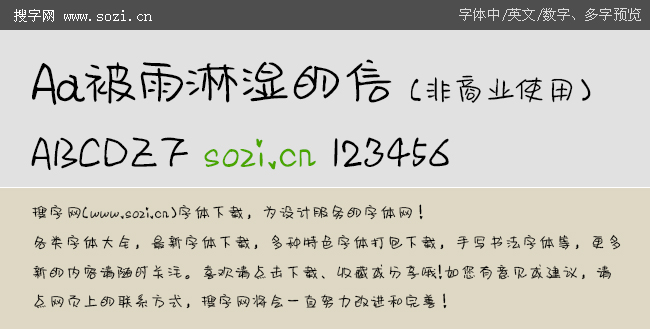
Aa被雨淋濕的信
搜字網(wǎng)給大家提供一款Aa被雨淋濕的信(非商業(yè)使用)中文字體下載,Aa被雨淋濕的信是一款卡通風格的手寫字體,這款字體筆畫略為纖細,字形圓潤可愛,富有趣味性,字體中部分英文的點被換成了可愛的愛心圖案,具有很好的視覺感。適合應用于藝術(shù)設(shè)計、平面宣傳設(shè)計、網(wǎng)頁設(shè)計、海報設(shè)計等應用(此字體為個人非商用版,商用可以聯(lián)系QQ:1006760504)。